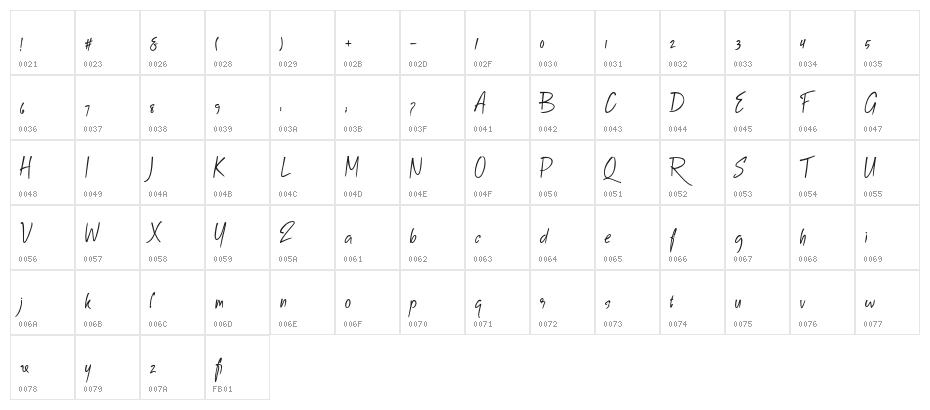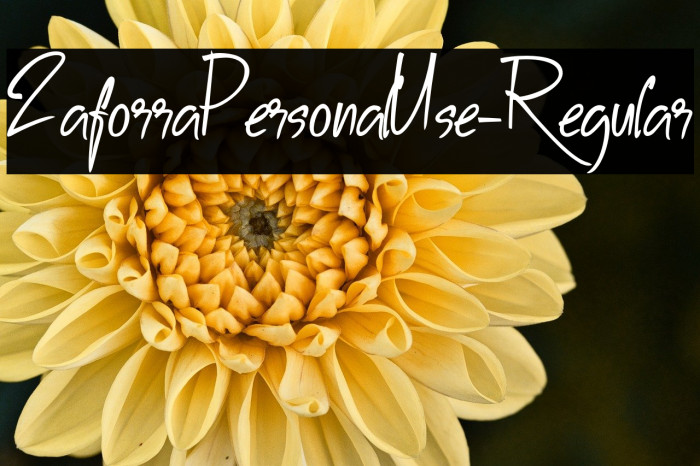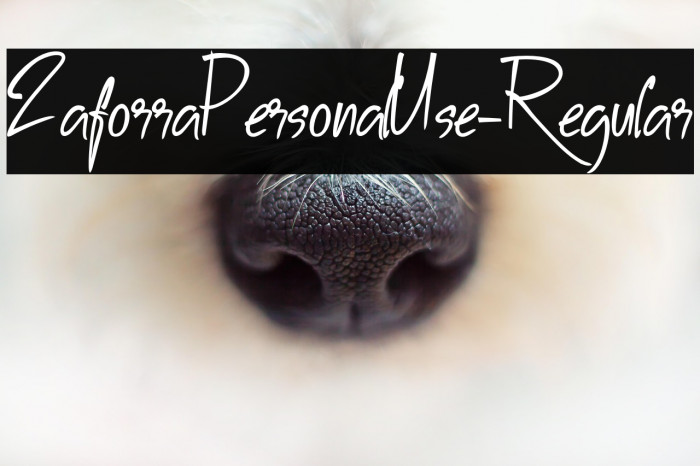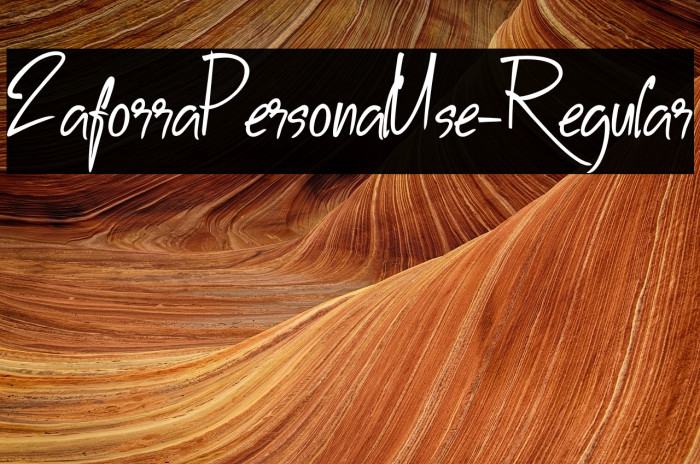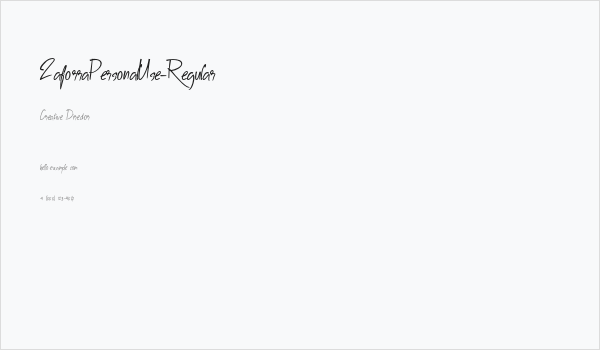
ZaforraPersonalUse-Regular Font
| حالة الاستخدام | Logos, Headlines, Artistic Projects |
| مشاريع مقترحة | Ideal for invitations, greeting cards, artistic posters, and branding materials that require a personal and creative touch. |